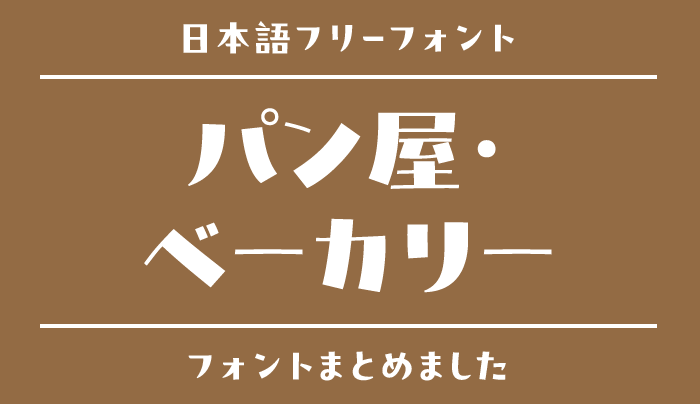
「パン屋・ベーカリー」にぴったりな日本語フリーフォント
焼きたてのパンの魅力を伝えるには、写真だけでなく商品名や店頭POPのフォントも大切です。丸くふっくらした文字なら親しみやすく、落ち着いた明朝なら素材や製法へのこだわりを丁寧に見せられます。
今回は、パン屋のショップカード、商品POP、季節商品の告知に使いやすい日本語フリーフォントを15個選びました。雰囲気をつくる文字と、価格・原材料などを読みやすく示す文字を分けて考えると、店の個性を伝えながら情報も整理できます。
パンのおいしさとお店の個性を伝えるフォント
くらむぼんフォント
収録文字ひらがな・カタカナ・漢字・英字・数字・記号
おすすめの場面焼きたて商品のPOP・新商品の大きな見出し
ふっくらした極太文字で、売り場を楽しく
くらむぼんフォントは、太い形に揺らぎのある輪郭を加えたフォントです。ふっくらしたパンの写真と合わせると、楽しく親しみやすい売り場の印象をつくれます。短い商品名や「焼きたて」の見出しを大きく組むのがおすすめです。価格や説明まで同じフォントにせず、情報用の文字を分けると商品の魅力が伝わりやすくなります。
カラメルホップ
おすすめの場面菓子パンの告知・かな中心の季節商品名
弾むような文字で、甘い商品の楽しさを
カラメルホップは、極太の形と跳ねるような傾きが特徴のフォントです。カタカナの商品名や短い呼びかけで、菓子パンの楽しさを前面に出せます。漢字は収録されていないため、商品名を実際に組んでから選んでください。説明用フォントはすっきりしたものにすると、見出しの元気な印象を残したまま読みやすくまとまります。
モボ
おすすめの場面ベーカリーのショップカード・商品カテゴリ見出し
角丸のゴシックで、今らしさと温かみを
モボは、角の丸さや墨だまりを持つゴシック系フォントです。現代的なベーカリーの紙面を、冷たくなりすぎずまとめたいときに合います。サンドイッチや食パンなどのカテゴリ見出しにも取り入れやすい表情です。店名風の文字を太めに、補足を軽めに組むなど、同じフォントの太さを使い分けると統一感が生まれます。
いろはマル
おすすめの場面町のパン屋のチラシ・定番商品のPOP
レトロな仮名で、いつもの店の親しみを
いろはマルは、丸い骨格に古風な仮名の流れを感じるフォントです。昔ながらの定番パンを紹介するPOPや、町のパン屋のチラシに合わせると温かい印象になります。レトロ感を強くしすぎたくない場合は、背景や飾りを簡潔にまとめましょう。丸ゴシックフォントのやさしさで、普段使いの店らしい空気をつくれます。
けいなんむぎまるJP
おすすめの場面親子向けの商品案内・やさしい印象のメニュー
丸い輪郭で、気軽に選べる売り場へ
けいなんむぎまるJPは、ゴシックの整った形を大きく崩さず角を丸めたフォントです。親子で選ぶパンの紹介や、やさしい印象にしたいメニューに向いています。個性的すぎないため、複数の商品を並べる紙面でも調和を取りやすくなります。価格の表示はサイズや位置を揃え、フォントの丸さと情報の見つけやすさを両立させましょう。
Rounded M+
おすすめの場面商品一覧・セット販売の案内
丸みの違いで、店の雰囲気を調整する
Rounded M+は、角の丸め方にバリエーションを持つフォントです。カジュアルな売り場には丸みを強めに、落ち着いた商品案内には控えめに選ぶなど、店の印象に合わせて試せます。商品名と価格に異なる太さを使えば、フォントを増やさず整理できます。小さなカードでは、線が太すぎて文字の内側がつぶれないか確認しましょう。
小杉丸(Kosugi Maru)
おすすめの場面商品説明カード・営業時間のお知らせ
控えめな丸さで、日常の案内を整える
小杉丸は、すっきりした形に丸みを持つフォントです。パンの商品説明や営業時間など、かわいさより先に内容を伝えたい部分に向いています。大きな商品名に別のフォントを使っても、補足を小杉丸で揃えるとまとまりが出ます。小さな売り場カードでは、文章を短くする工夫と十分な文字サイズも合わせて考えると効果的です。
はる手書きフォント
おすすめの場面スタッフのおすすめ・焼き上がりのひとこと
手書きの声で、パンへの思いを伝える
はる手書きフォントは、細く丁寧な手書きの表情を持つフォントです。スタッフのおすすめや食べ方のひとことを添えると、パンを選ぶ時間に親しみが生まれます。長い説明をすべて手書きにするより、短いコメントで活かすのがおすすめです。値札の数字は別のフォントで明瞭に示し、会話のような温度感だけを加えましょう。
きろ字
おすすめの場面パンの紹介カード・店だより
整った手書きで、商品の話を身近に
きろ字は、自然な手書き感と落ち着いた形を併せ持つフォントです。商品の生まれた背景や店の小さな出来事を伝えるカードに使うと、丁寧で親しみやすい印象になります。短い段落をゆったり配置すれば、手書きの温かさを保てます。必要な商品情報とは欄を分け、読み物の部分にフォントの個性を活かしてみてください。
はちまるポップ(Hachi Maru Pop)
おすすめの場面懐かしい菓子パンの企画・限定フェアの見出し
丸文字の懐かしさで、楽しい商品企画に
はちまるポップは、昔の丸文字を思わせるフォントです。懐かしい菓子パンを集めたフェアや、遊び心のある限定企画の見出しに合わせやすくなっています。文字の丸さが強いので、短い商品名を大きめに見せる使い方が効果的です。価格や補足は落ち着いたフォントで揃えると、企画の楽しさが過剰にならず伝わります。
しっぽり明朝
おすすめの場面素材を紹介するリーフレット・落ち着いた店のカード
柔らかな明朝で、素材へのこだわりを
しっぽり明朝は、丸みや墨だまりの表情がある明朝フォントです。小麦や製法について丁寧に紹介する紙面に使うと、親しみを残しながら落ち着いた印象になります。パンの写真と短い見出しを余白のある構成で組むと、文字の風合いが活きます。細かな原材料表示は別の読みやすいフォントに分け、説明の役割を整理しましょう。
アプリ明朝
おすすめの場面製法の紹介冊子・季節のパンの読みもの
明朝の落ち着きを、堅すぎない表情で
アプリ明朝は、ウロコや止めの処理をやわらかくしたフォントです。発酵や焼き方など、店の考え方を文章で紹介する小冊子に向いています。高級感だけに寄せず、素直に読める紙面にしたいときの候補です。大きなタイトルは少し太く、本文は余裕のある行間にすると、同じ明朝フォントでも役割の違いが伝わります。
源雲明朝